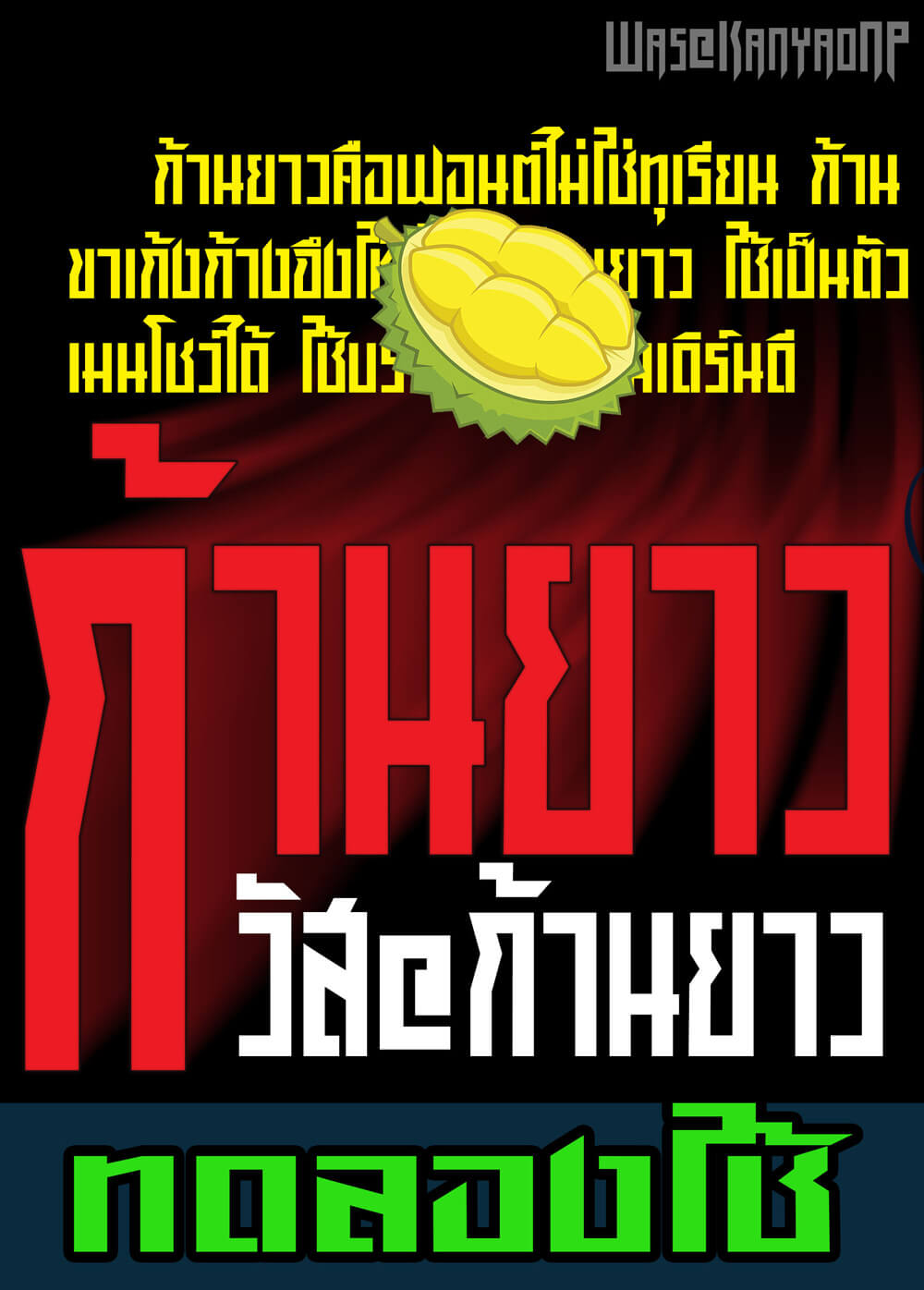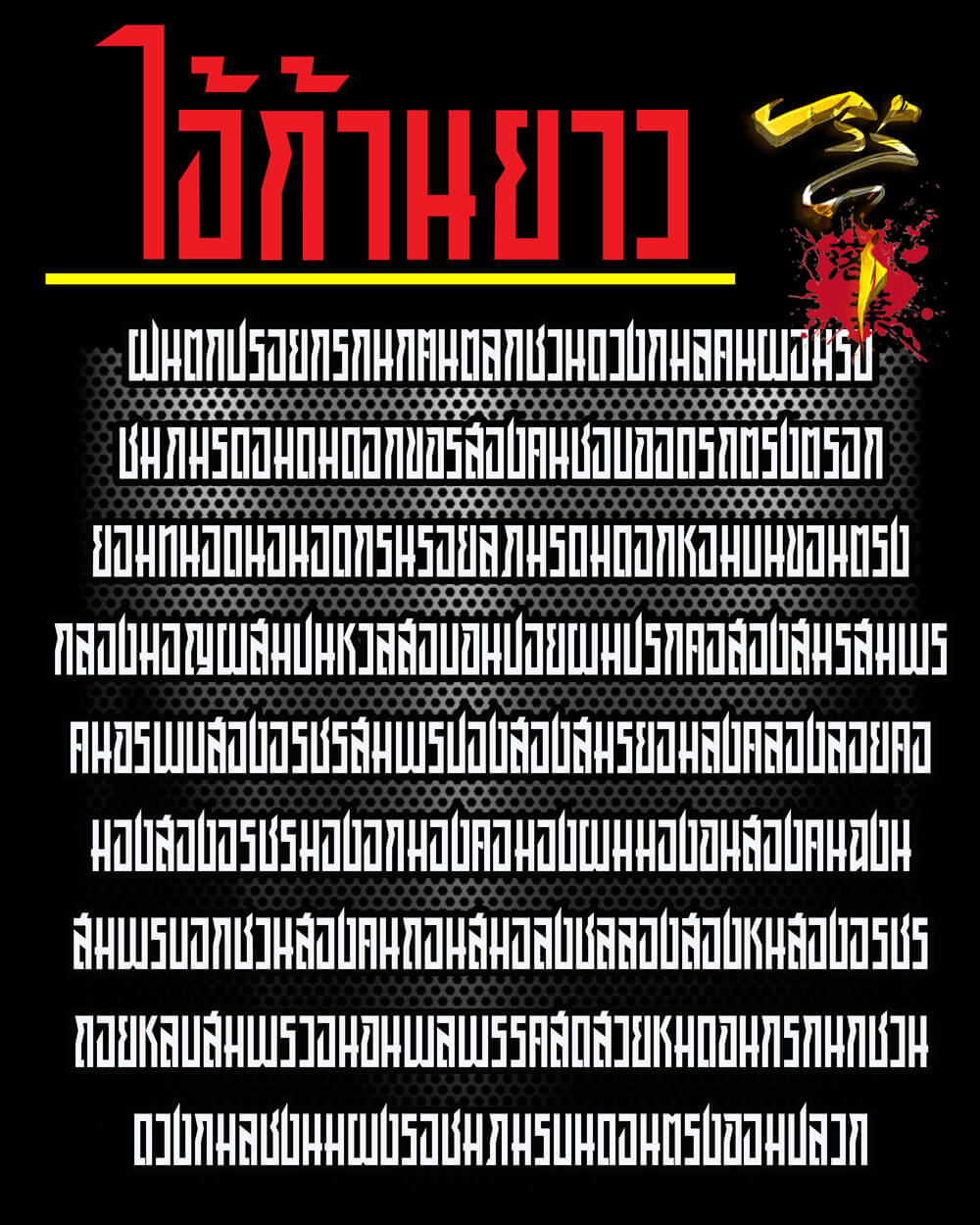
was@kanyao (วัส@ก้านยาว)
ฟอนต์สไตล์ก้านยาวของน้าวัสมาอีกแล้วครับ ตัวนี้ทดลองใช้เช่นเคยนะครับ มีบั๊กอยู่นิดหน่อย ถ้าอยากใช้เต็มๆ ติดต่อสอบถามได้ที่เพจด้านล่างครับ ราคา 300 บาท
ฟอนต์: was@kanyao (วัส@ก้านยาว)